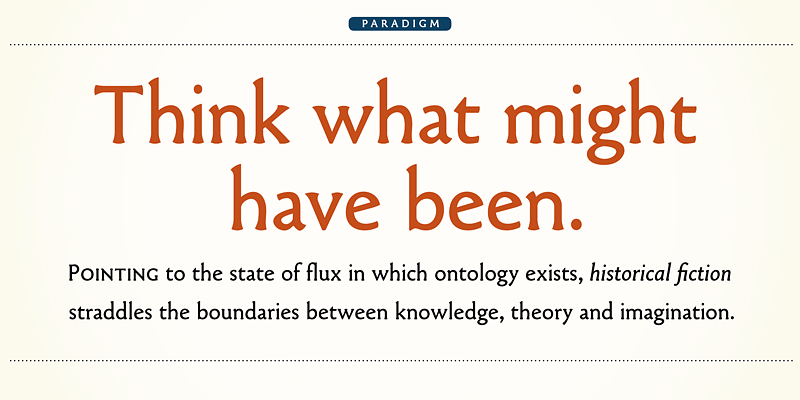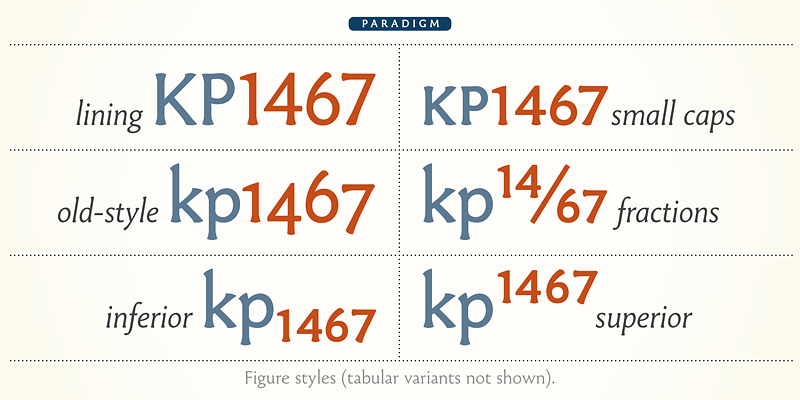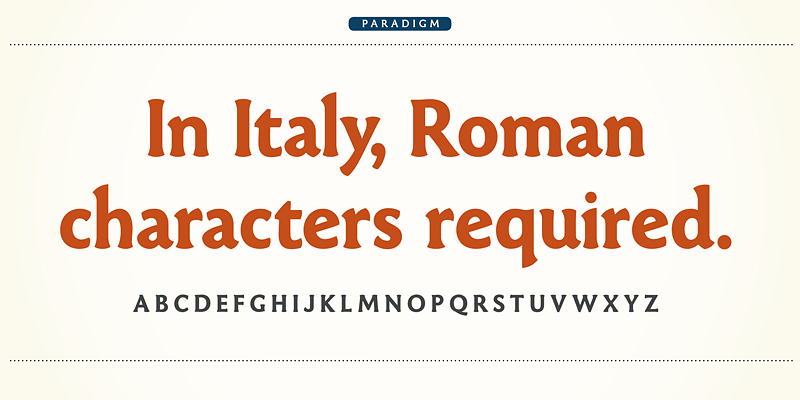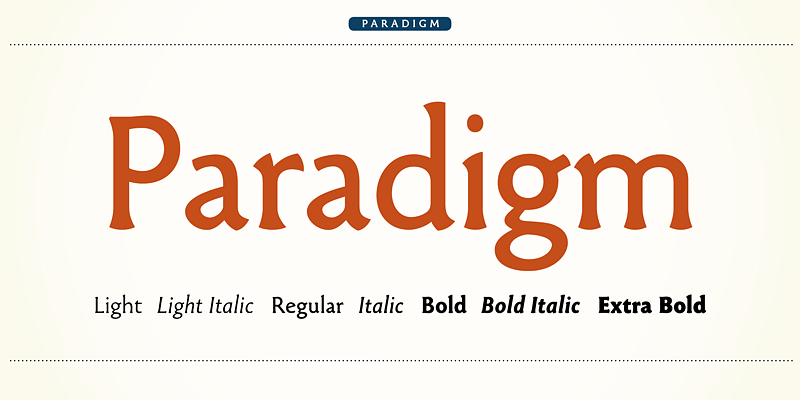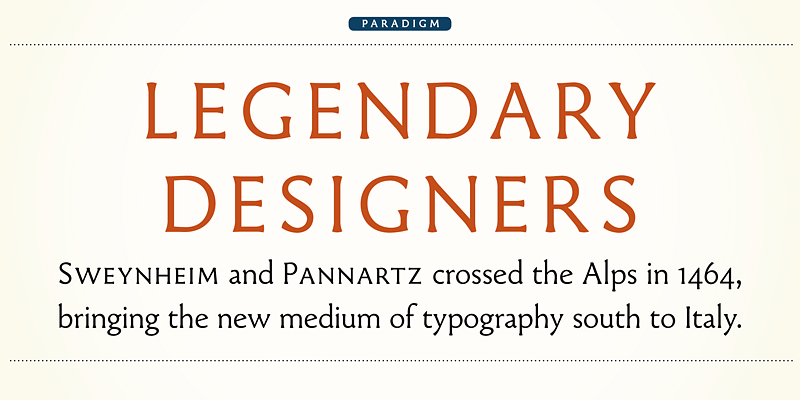
La première véritable police de style romain (par Konrad Sweynheim et Arnold Pannartz en 1468) possédait de grands empattements sur les lettres majuscules, mais pratiquement aucun sur les minuscules. Le traitement de la casse fut intégré peu de temps après, les empattements dominant les 350 années suivantes. Ici, Nick Shinn emprunte de nouveaux chemins, changeant l’accent pour imaginer une police dans l’ancien style vénitien avec des empattements rudimentaires et très peu contrastés, nous obligeant à imaginer le champ des possibles, semant la confusion entre ce qui est, et aurait pu être ; une construction subversive qui expose le caractère changeant de l’authenticité culturelle.
Telles sont les conceptions de Nick Shinn : profondément enracinées dans l’évolution continue de la meilleure tradition typographique européenne et nord-américaine, solidement ancrées dans le texte, offrant toutes les caractéristiques d’une typographie experte, élégantes, et portant une attention incomparable aux détails.
Fort de son expérience de directeur artistique et de graphiste acquise dans les 80 et 90, ayant compté parmi les premiers à travailler sur les médias numériques, Nick Shinn a lancé Shinntype, l’une des premières fonderies de caractères en ligne, en 1998. Shinntype dispose aujourd’hui d’un important catalogue très éclectique de polices uniques, adaptées aux tendances contemporaines.